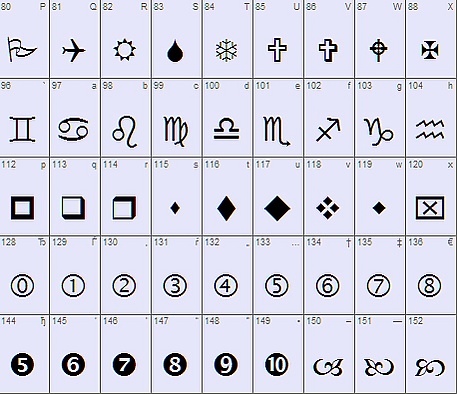
Символьный шрифт
Символьный шрифт — разновидность шрифтов, состоящих из знаков, не имеющих отношения к алфавиту и не входящих в основной комплект шрифта.
«Обычно это пиктограммы: миниатюрные изображения телефонов, лыжников, самолётов, церквей и прочих атрибутов туристического бизнеса. Другие — более абстрактные символы: декоративные элементы, орнаменты, стрелки, буллиты и т. д.»[1]
По умолчанию в ОС Windows загружено несколько символьных шрифтов, среди которых наиболее часто используются Wingdings и Webdings.